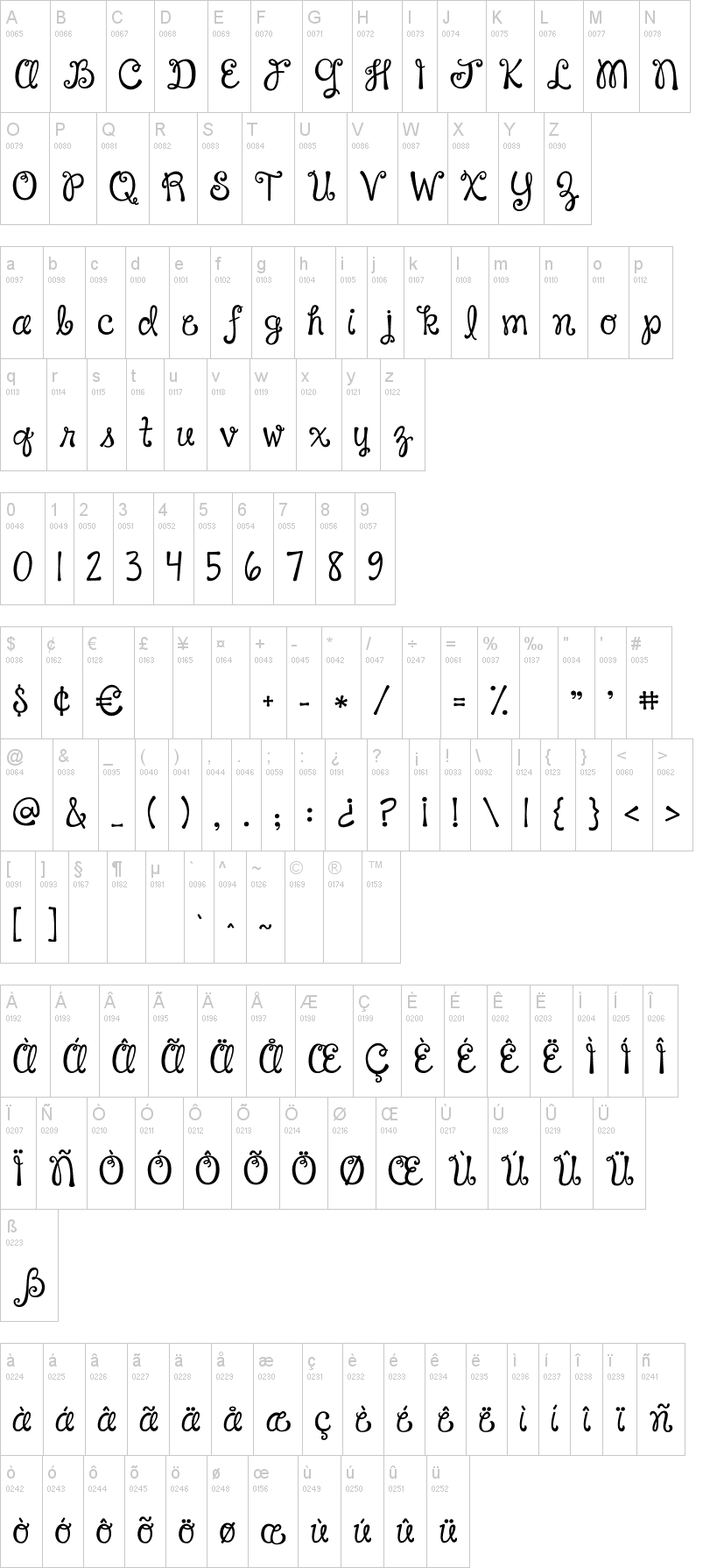
Janda Happy Day 是由 Kimberly Geswein 创作的一款手写字体,它具有温暖、活泼、有趣的特点。它的字体特点是每个字母都有自己的细节,比如折叠、蜿蜒、活力十足,极具特色。这款字体能够很好地表达出欢乐、激情、快乐的情绪,适用于各种场景,比如婚礼、宣传海报、广告等。内容介绍
Janda Happy Day是一款非常不错的手写艺术字体,具有很好的视觉感,适合于文化类的宣传设计、商业类品牌的广告和产品包装设计以及个性化文字排版等较多场景。